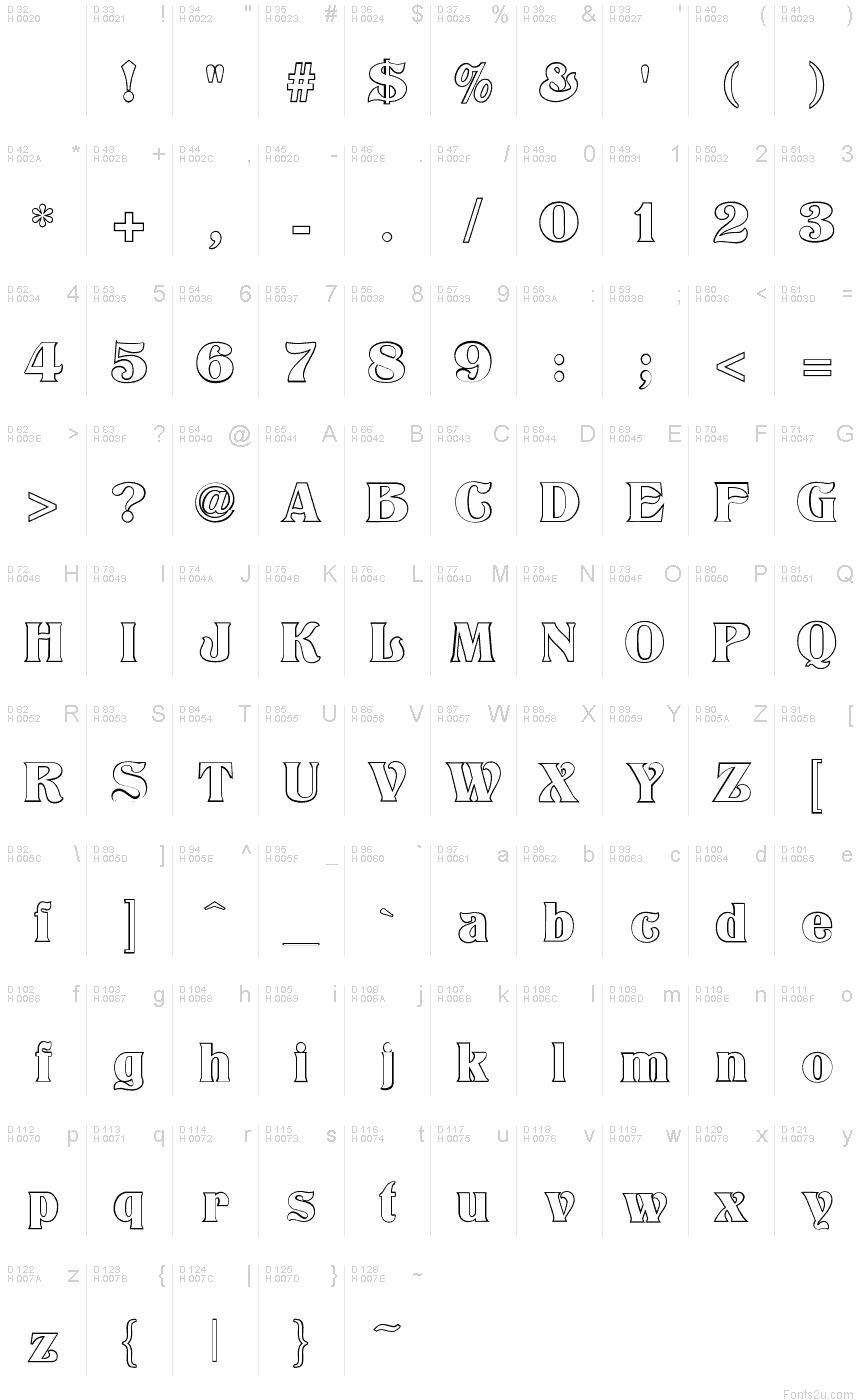
Podgląd czcionki Titania Outline
Titania Outline od Typographer Mediengestaltung to darmowy, konturowy krój szeryfowy z nutą baśniowego, nieco średniowiecznego klimatu. Litery łączą miękkie, pełne krzywizny z wysokimi, klinowatymi szeryfami, dzięki czemu font jest ozdobny, ale nieprzeładowany, a otwarty kontur dodaje tej dekoracyjnej formie lekkości.
Naturalnie wpisuje się w opakowania, okładki książek, branding kawiarni, plakaty i nagłówki, wszędzie tam, gdzie przyda się odrobina uroku dawnych lat. Ten darmowy font świetnie sprawdza się również w monogramach lub krótkich hasłach. Sięgnij po niego, gdy chcesz, by same litery budowały nastrój – dzięki konturom i baśniowym szeryfom nawet krótkie słowa zyskują elegancką, niemal emblematyczną oprawę.